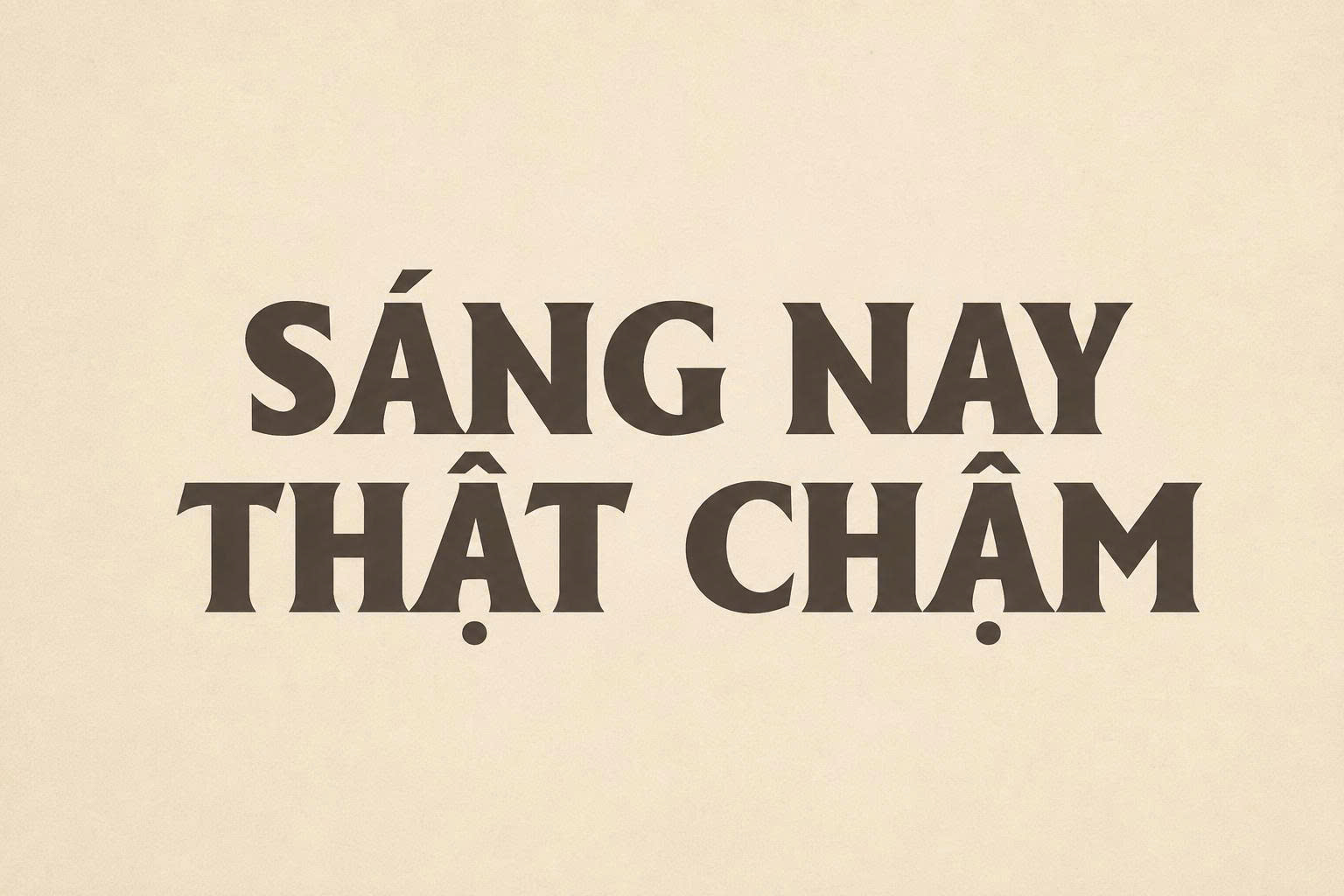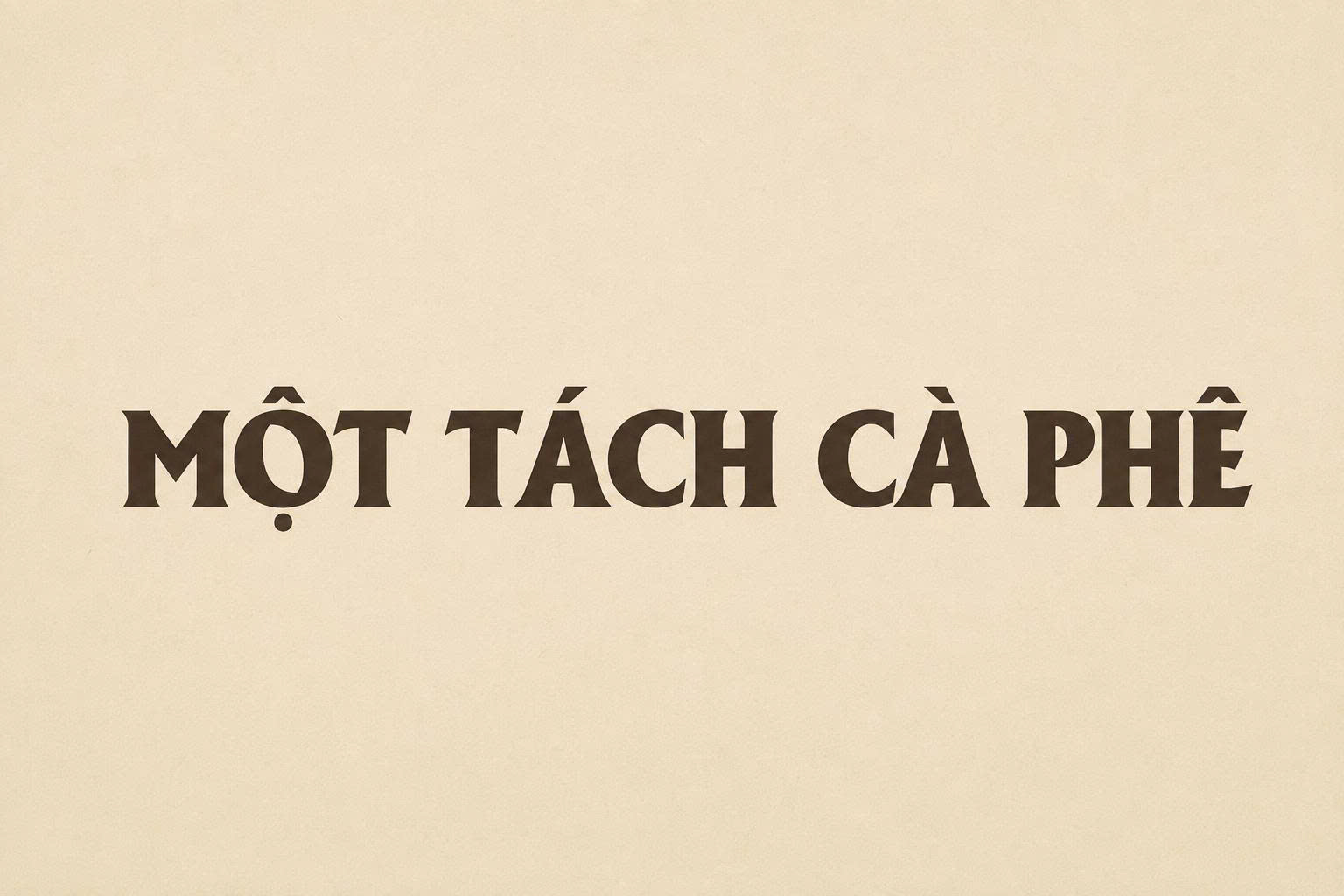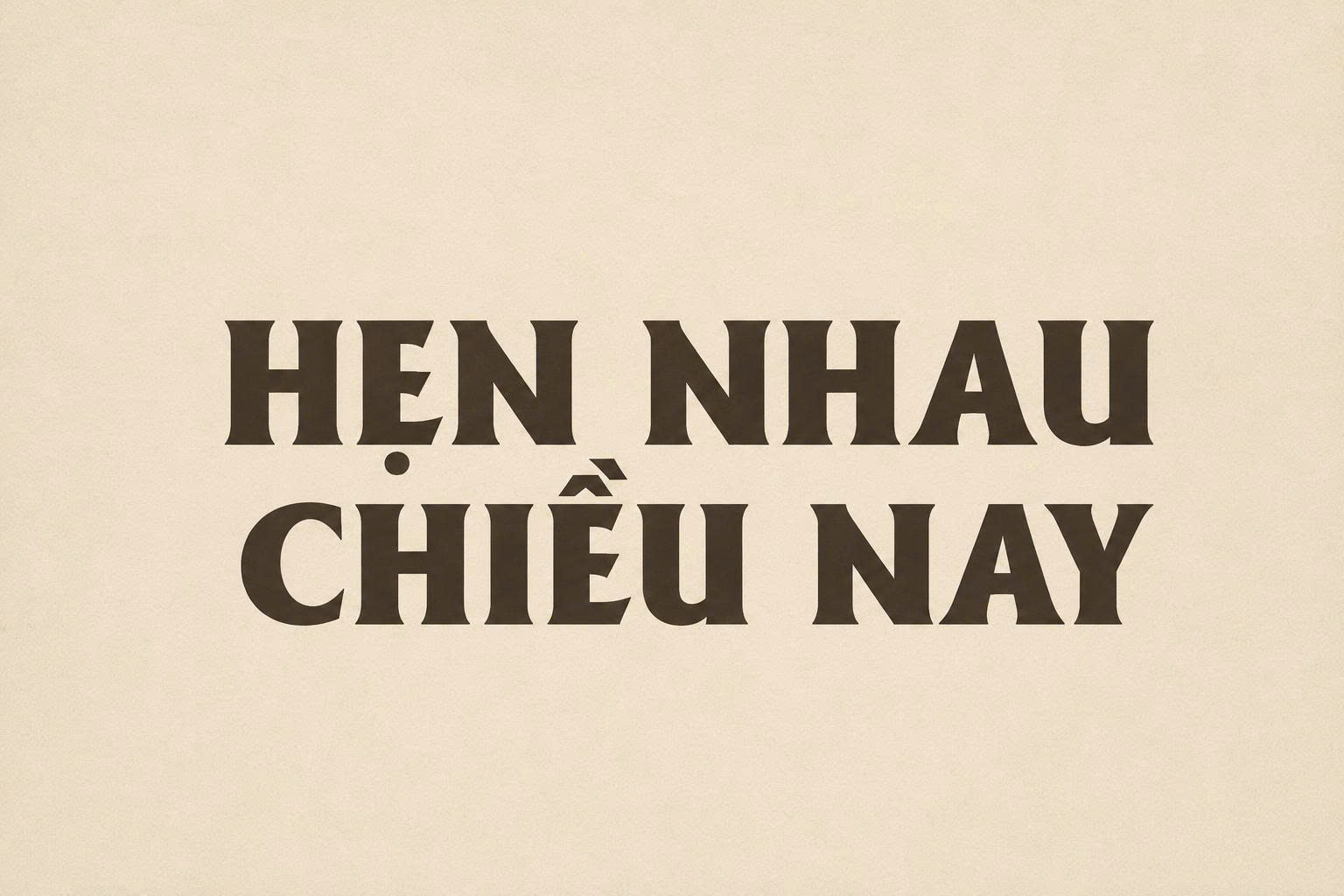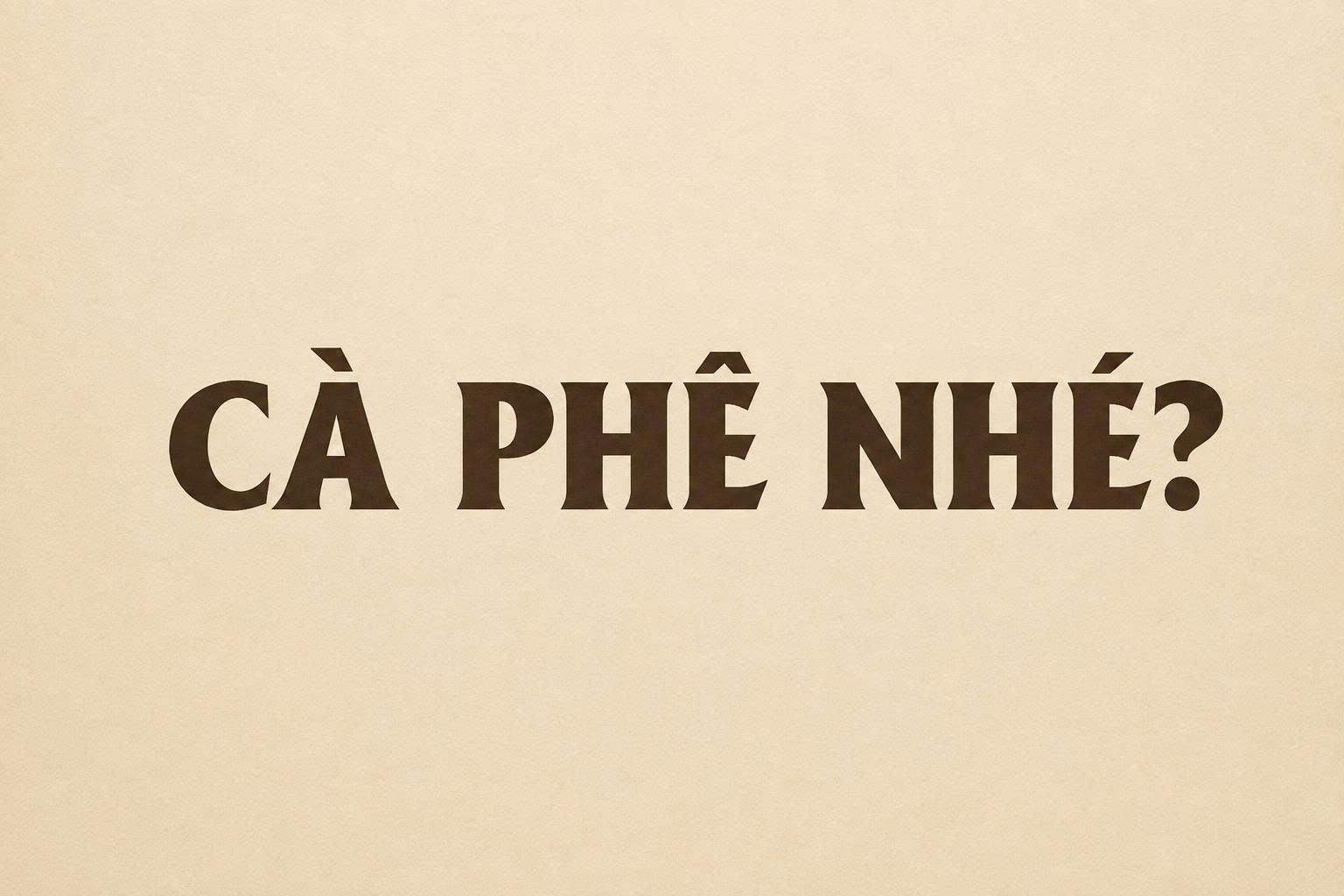
Font Việt hóa UTM Alberta Heavy là bộ phông chữ thuộc dòng Sans-serif (không chân) nổi bật với cấu trúc nét dày, vững chãi và mang đậm tính hình học hiện đại. Trong hệ thống font UTM kinh điển, Alberta Heavy luôn là lựa chọn hàng đầu cho các thiết kế tiêu đề, logo hoặc bao bì cần sự mạnh mẽ, rõ ràng và thu hút thị giác ngay lập tức. Doozypack.vn cung cấp link font utm alberta heavy free download chuẩn, giúp bạn sở hữu bộ font chữ việt hóa utm alberta heavy chỉn chu, hỗ trợ đầy đủ bảng mã tiếng Việt để phục vụ các dự án thiết kế và in ấn chuyên nghiệp.
Đặc điểm nổi bật của font chữ việt hóa UTM Alberta Heavy
UTM Alberta Heavy không chỉ đơn thuần là một phông chữ đậm màu, nó sở hữu những đặc tính thiết kế giúp bản thiết kế của bạn trở nên uy tín và hiện đại hơn.
Cấu trúc nét Bold dày dặn và cân đối
Đặc trưng lớn nhất của font việt hóa utm alberta heavy là độ dày nét chữ đồng nhất, tạo nên một khối văn bản vững chắc. Các ký tự được thiết kế với độ tương phản thấp, các góc chữ sắc sảo mang lại cảm giác minh bạch và quyết đoán. Điều này giúp bộ font giữ được độ rõ nét đáng kinh ngạc ngay cả khi người dùng quan sát từ khoảng cách xa.
Hệ thống dấu tiếng Việt chuẩn hóa của bộ UTM
Nằm trong bộ sưu tập font UTM (Umitimes) nổi tiếng, Alberta Heavy đã được tối ưu hóa hoàn toàn cho người dùng Việt Nam. Các dấu thanh được đặt ở vị trí cân đối, không làm thay đổi chiều cao của dòng chữ, giúp việc dàn trang trên bao bì hay website trở nên dễ dàng và đạt độ thẩm mỹ cao nhất.
03 Lý do designer nên chọn font UTM Alberta Heavy cho thiết kế bao bì?
Trong ngành in ấn bao bì tại Doozypack.vn, Alberta Heavy luôn là “ngôi sao” cho các vị trí cần tạo điểm nhấn:
- Tăng cường khả năng nhận diện: Với độ Bold mạnh mẽ, font chữ này giúp tên thương hiệu trên túi giấy hay hộp quà nổi bật hoàn toàn giữa các họa tiết trang trí.
- Tính đa dụng cao: Bạn có thể sử dụng Alberta Heavy cho nhiều phong cách từ hiện đại, công nghiệp đến tối giản.
Lời khuyên từ xưởng in: Đối với các bản thiết kế in trên giấy có độ thấm mực cao như giấy Kraft nhám, Alberta Heavy là lựa chọn an toàn. Tuy nhiên, bạn nên tăng nhẹ khoảng cách chữ (Tracking) để tránh hiện tượng mực bị lan làm bít các khe chữ nhỏ.
03 Ứng dụng của font UTM Alberta Heavy trong in ấn tại Doozypack.vn
Tại xưởng sản xuất của Doozypack.vn, Alberta Heavy thường xuyên xuất hiện trên các ấn phẩm thực tế:
- In túi giấy doanh nghiệp: Tên công ty sử dụng Alberta Heavy tạo cảm giác vững chắc và uy tín khi in khổ lớn trên túi giấy Ivory cán màng.
- Hộp cứng quà tặng: Slogan hoặc thông điệp chính in bằng font Alberta Heavy kết hợp kỹ thuật ép kim mờ tạo nên vẻ ngoài vô cùng hiện đại.
- Tem nhãn sản phẩm: Phù hợp cho các dòng sản phẩm công nghệ, linh kiện điện tử hoặc thực phẩm cần sự minh bạch thông tin.
- Kiểm soát hiện tượng Dot Gain (Tràn mực): Nét chữ Bold dày dễ bị “mập” hơn sau khi in. Designer nên kiểm tra kỹ các ký tự có khoảng hở hẹp như ‘e’, ‘a’, ‘g’ để đảm bảo chúng không bị dính nét.